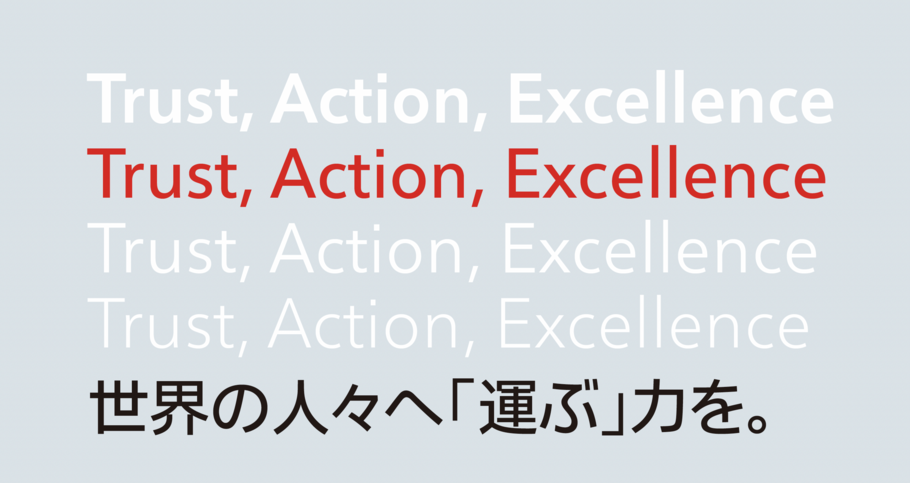
機能性とブランドを考慮したいすゞ自動車の専用書体
Monotypeは、世界トップクラスの商用車メーカー、いすゞ自動車株式会社の専用書体を制作しました。
いすゞ自動車株式会社は、1916年に創業した、グローバルに事業展開している日本企業です。主にバス、トラック、産業用エンジンなどを製造しています。時代の変化にともない、車載機器の画面に多様な情報を表示するためのコンパクトな書体が必要とされていました。また、多言語展開や和文欧文併記をする機会が増えたことにより、それらに対応した書体のニーズも高まっていました。
そうした背景から、いすゞ自動車とMonotypeで専用書体の方向性について検討。長く使える普遍性、コンパクトな骨格、ウェイトの豊富さ、可読性、和欧混植時の調和などの機能的な条件と、信頼、誠実、クリーンなブランドイメージを考慮し、スタンダードな佇まいの中にもやや硬質で整然とした雰囲気のある専用書体を制作することになりました。
欧文書体については、社内で使用していたAvenir Nextの硬質な印象を残しながら、画面上での可読性や実用性を考慮して調整。Light、Regular、Medium、Demiの4ウェイトにそれぞれコンデンスを加えた8ウェイトの専用書体Isuzu ANを制作しました。Avenir Next の多言語ファミリーを使用したよりグローバルな展開も可能です。また和文書体には、Avenir NextにあわせてMonotypeが開発したShorai Sansを採用。視認性が高く、機器の表示にも適した書体です。Isuzu ANと組み合わせて使える4ウェイトが指定されました。
いすゞ自動車の専用書体は、機能性とブランドを兼ね備えた書体として、同社の製品やメッセージに幅広く使われる予定です。